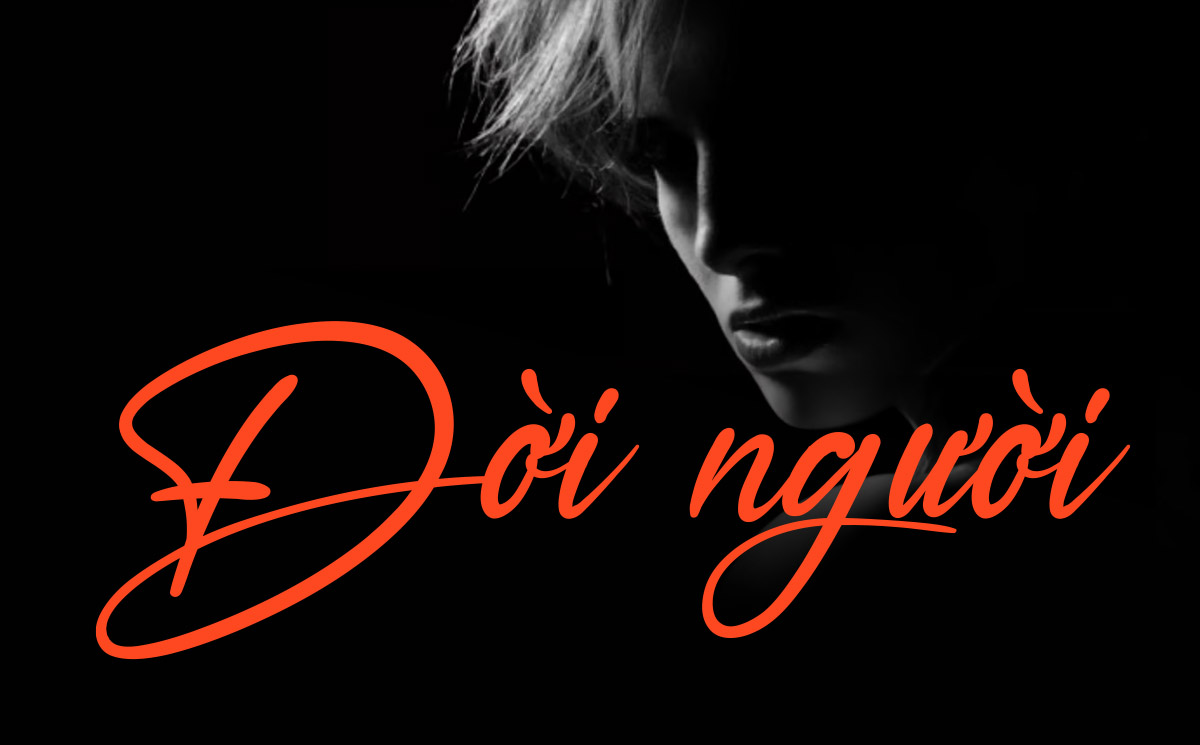
Font SVN Ameyallinda Signature Việt Hóa Chữ Ký Mềm Mại Dành Cho Thiệp Cưới
Font SVN Ameyallinda Signature Việt Hóa: Chữ Ký Mềm Mại Dành Cho Thiệp Cưới
Trong thiết kế đồ họa, đặc biệt là các ấn phẩm mang tính cá nhân và lãng mạn như thiệp cưới, việc lựa chọn đúng phông chữ đóng vai trò vô cùng quan trọng. Nếu bạn đang tìm kiếm một bộ font chữ viết tay mang đậm chất nghệ thuật, SVN Ameyallinda Signature chắc chắn là mảnh ghép hoàn hảo. Với các đường nét chữ ký mềm mại, bay bổng, bộ phông chữ Việt hóa này sẽ biến mọi thiết kế của bạn trở nên tinh tế và sang trọng hơn bao giờ hết.
Thông tin tổng quan về Font SVN Ameyallinda Signature
Ameyallinda Signature là một phông chữ dạng script (chữ viết tay) được thiết kế mô phỏng lại nét bút ký tự nhiên. Phiên bản SVN Ameyallinda Signature đã được Việt hóa chỉn chu, căn chỉnh lại các dấu câu và ký tự để phù hợp hoàn toàn với bộ gõ tiếng Việt.
• Phong cách: Viết tay (Handwritten), Chữ ký (Signature), Lãng mạn, Thanh lịch.
Vì sao nên chọn SVN Ameyallinda Signature cho thiết kế đám cưới?
Thiệp cưới không chỉ là tấm vé mời mà còn là thông điệp tình yêu của cô dâu và chú rể. Dưới đây là những lý do phông chữ này luôn được các designer săn đón:
1. Đường nét chữ ký tự nhiên, mềm mại
Khác với những font script quá cứng nhắc, Ameyallinda Signature sở hữu nét thanh nét đậm uyển chuyển, mô phỏng hoàn hảo lực nhấn của bút mực. Các ký tự có sự liên kết liền mạch, tạo ra một tổng thể chữ ký đẹp mắt, mang đậm dấu ấn cá nhân.
2. Dấu tiếng Việt được xử lý tinh tế
Điểm yếu của nhiều font ngoại nhập là lỗi hiển thị khi gõ tiếng Việt. Tuy nhiên, bản Việt hóa SVN đã khắc phục triệt để vấn đề này. Các dấu câu (huyền, sắc, hỏi, ngã, nặng) được đặt ở vị trí cân đối, không bị chồng chéo lên các nét vuốt cong (swashes) của chữ cái.
3. Đa năng trong ứng dụng thiết kế
Không chỉ gói gọn trong thiệp cưới, font chữ này còn cực kỳ tỏa sáng khi được ứng dụng vào:
• Welcome Board (Bảng tên đón khách): Tạo sự chú ý và sang trọng ngay từ sảnh tiệc.
• Album Ảnh Cưới (Photobook): Làm Typography cho các câu quote tình yêu, chèn vào các góc ảnh nghệ thuật.
• Logo cá nhân: Thiết kế logo chữ ký lồng ghép tên cô dâu – chú rể (Monogram).
• Thiết kế thiệp chúc mừng, menu tiệc: Tăng thêm phần lãng mạn và đẳng cấp cho bàn tiệc.
Bí quyết kết hợp phông chữ (Font Pairing) hiệu quả
Để SVN Ameyallinda Signature thật sự nổi bật trên trang thiệp, bạn không nên sử dụng nó cho toàn bộ văn bản. Hãy dùng font chữ này cho những nội dung chính cần điểm nhấn như: Tên cô dâu chú rể, hoặc chữ “Save the Date”.
Đối với các đoạn thông tin chi tiết (ngày giờ, địa điểm), hãy kết hợp với các phông chữ Serif (có chân) thanh lịch hoặc Sans-serif (không chân) tối giản, rõ ràng. Sự tương phản này sẽ giúp bố cục thiệp cưới trở nên hài hòa và dễ đọc hơn.